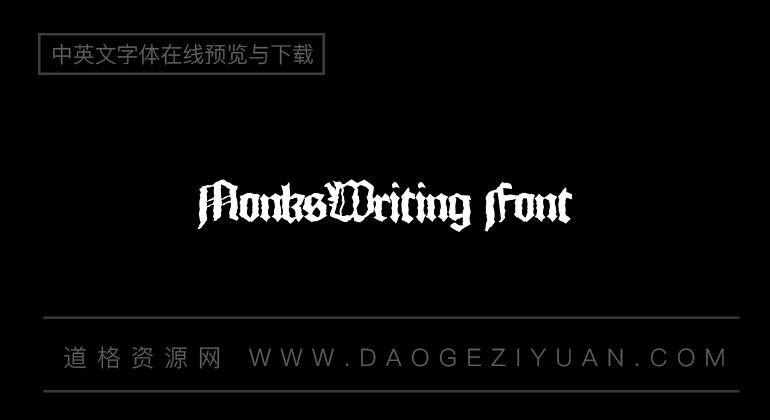
MonksWriting Font 是一种由字形设计师 Fernando Haro 设计的手写字体。它的设计灵感来自于中世纪时期修道院内的手写文献。该字体融合了传统风格和现代风格,给人一种古老而又时尚的感觉。 MonksWriting Font 的每个字母都被设计成类似手写的字体,具有自然、流畅、有机的特点,这使得它非常适合用于正式和半正式的场合,如书信、邀请函、名片等。此外,它还可以用于设计领域,如海报、广告、标志等。 MonksWriting Font 有多种字重和样式,包括常规、粗体、斜体和粗斜体。它支持多种不同的语言和字符集,包括西欧语言、中欧语言、斯堪的纳维亚语言、希腊语、土耳其语等。此外,它还支持 OpenType 特性,如字形变化、连字等,这使得它更加灵活和多功能。 总的来说,MonksWriting Font 是一种独特的、多功能的手写字体,适用于各种不同的场合和设计领域。内容介绍
MonksWriting Font是一款非常不错的手写艺术字体,具有很好的视觉感,适合于文化类的宣传设计、商业类品牌的广告和产品包装设计以及个性化文字排版等较多场景。